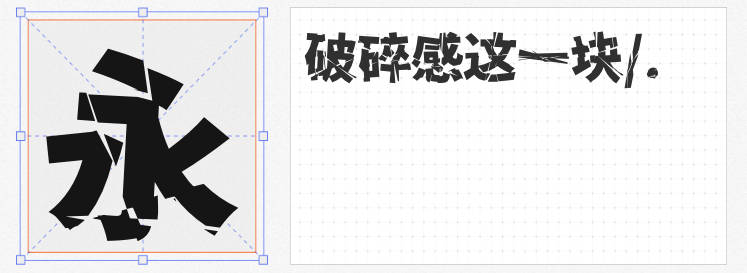
在视觉设计同质化的今天,一款独具创意的字体往往能成为作品的点睛之笔。然而,商用字体的版权成本常让设计师望而却步。本文精选四款免费可商用的创意字体,涵盖字形重构、手写趣味、书法新解与解构实验四大方向,助你轻松打造令人过目难忘的视觉语言。
源自日本「解星计划」的衍生字型,小狼天穹以「宇文天穹」为基底,通过补全繁简体字与注音符号,构建出兼具学术严谨性与设计美感的完整字库。其字形保留传承字形的结构精髓,笔画粗细过渡如手写般自然,却以更简洁的轮廓适配现代屏幕显示。适合文化类、教育类项目,或需要传递历史厚重感的设计场景,让传统文字焕发新生。
这款字体以“随性不拘谨”为灵魂,字形饱满如孩童涂鸦,笔画错落中暗藏黄金比例:横竖粗细对比强烈,局部高光纹理模拟纸张反光效果,仿佛墨迹未干时的自然肌理。无论是儿童品牌LOGO、社交媒体标题,还是生活类海报正文,文心喜乐体都能以温暖萌态拉近与受众的距离,让信息传递更具人情味。
以传统书法为骨,融入锐意进取的现代美学,启航体的笔画如刀刻般遒劲,笔锋向上扬起,暗喻“勇立潮头”的企业精神。作为公益开放的字体,它不仅适用于励志标语、文化传播项目,更能通过字形传递积极价值观。无论是科技公司的品牌宣言,还是校园活动的主题海报,启航体都能以力量感激发受众共鸣。
源自日文字体「零ゴシック」的简化字版本,香萃零度黑以扭曲、分裂的笔画设计颠覆传统:远观如流畅曲线,近看则棱角分明,切口处的直线与曲线碰撞出未来感。作为装饰性字体,它适合科技、潮流、艺术类设计的标题或点缀元素,部分保留的日式汉字特征更增添异域设计张力,让作品瞬间脱颖而出。
从传统字形的现代转译,到书法精神的先锋表达,这四款字体以免费商用与高创意价值的双重优势,为设计师提供了更多表达可能。无论追求文化深度、情感温度,还是视觉冲击力,它们都能成为你突破设计瓶颈的秘密武器。